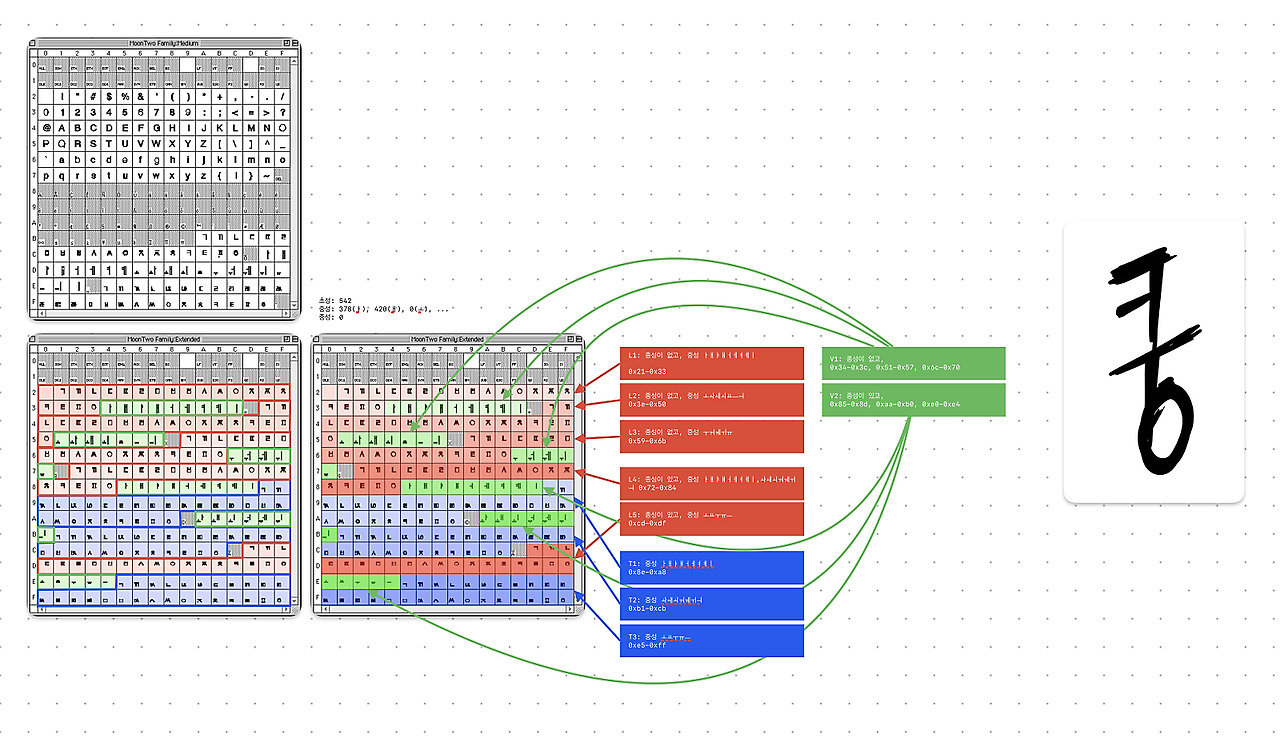
웹툰용 직결식 만화폰트 제작 솔루션 개발
이 솔루션은 만화와 관련된 특화된 폰트를 제작하고 이를 활용한 굿즈를 판매하는 강력한 도구가 될 수 있습니다. 이를 성공적으로 실행하기 위해 다음과 같은 발전 방향과 추가적인 요소를 고려할 수 있습니다.
1. 직결식 폰트 시스템 확장
• 자동화된 위치 조정:
• 초성, 중성, 종성을 기반으로 한 위치 조정 로직을 세밀하게 설정.
• 방사형 배치에 따라 각 초성, 중성, 종성이 자연스럽게 조화를 이루도록 패턴과 알고리즘 개발.
• 패밀리 폰트 확장:
• 한 번에 20여 개의 패밀리 폰트를 자동 생성할 수 있도록 직결식 시스템을 최적화.
• 다양한 스타일 옵션(굵기, 경사, 곡선 등)을 추가하여 굿즈 제작에 적합한 폰트를 확장.
3. 템플릿 및 인터페이스 강화
• 템플릿 확장:
• 기본 SVG 템플릿을 세부 작업이 가능한 고급 템플릿으로 확대.
• 초성, 중성, 종성의 배치를 세밀하게 조정할 수 있는 옵션 추가.
• UI/UX 설계:
• 각도를 기준으로 하는 UI 설계.
• 사용자가 방사형 배치, 크기, 위치를 직관적으로 조정할 수 있는 그래픽 툴 개발.
4. 만화 기반 폰트의 차별화 전략
• 방사형 폰트의 예술적 가치 부각:
• 만화 특유의 표현 방식에 맞춘 폰트의 독창성을 홍보.
• 방사형 폰트가 일반적인 폰트와 어떻게 차별화되는지 사례를 통해 설명.
• 스토리텔링 연계:
• 만화 캐릭터나 특정 작품의 스타일을 반영한 폰트 제작.
• 특정 폰트를 사용하는 팬 굿즈에 해당 작품과의 연계를 더해 부가가치 창출.
5. SVG 기반 솔루션의 미래 개발
• SVG에서 OTF/TTF 변환:
• 현재 SVG 템플릿 기반에서 완성된 폰트를 TTF/OTF 형식으로 변환하는 기능 추가.
• 폰트를 다양한 플랫폼에서 사용 가능하게 확장.
• SVG 애니메이션 활용:
• 폰트를 기반으로 한 애니메이션 콘텐츠 제작 지원.
• 만화 속 방사형 대사가 애니메이션으로 표현되도록 연결.
장기적인 비전
• 만화와 타이포그래피의 융합으로 새로운 창작 트렌드 형성.
• 방사형 글꼴 디자인을 중심으로 한글 폰트의 예술적, 상업적 가치 확대.
• 독창적인 폰트와 굿즈 제작을 통해 만화 팬들과 디자이너 커뮤니티의 연결 강화.